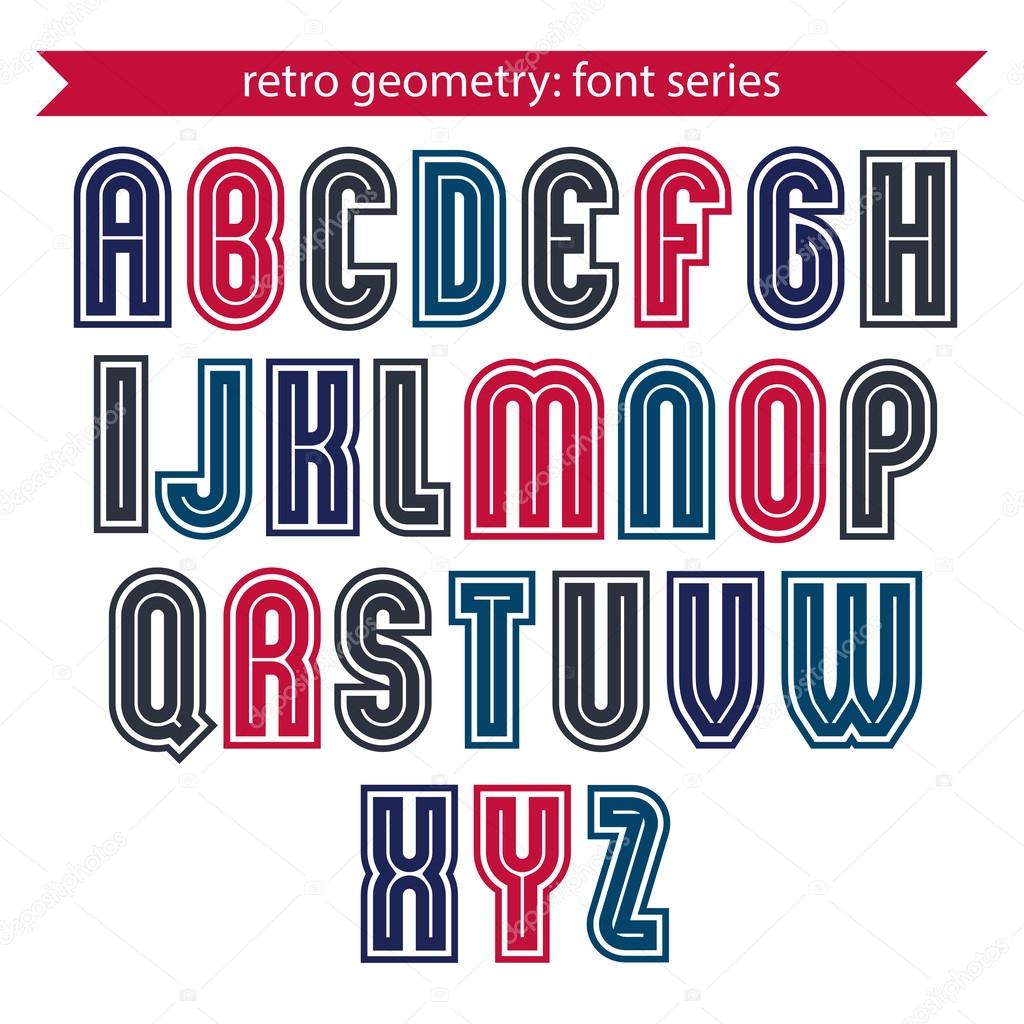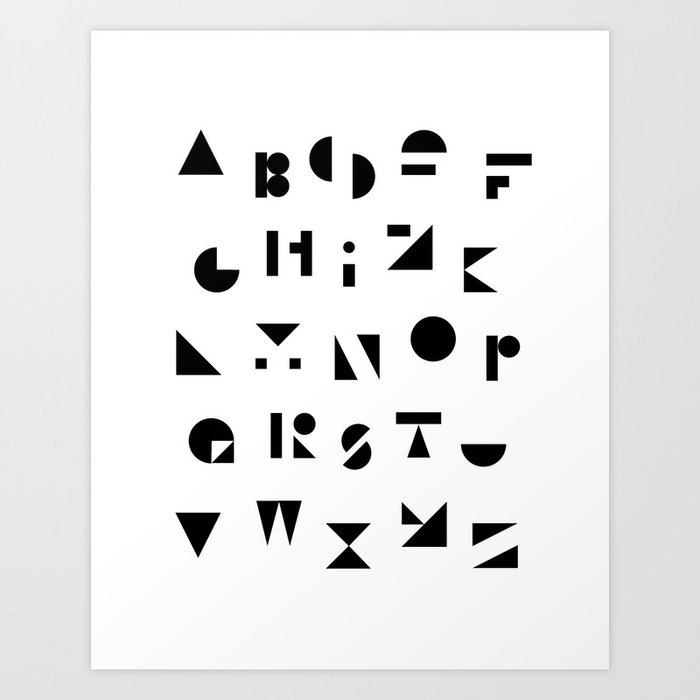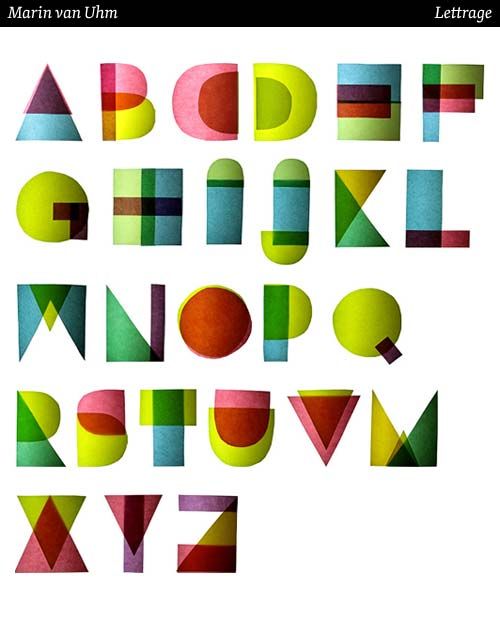
Геометрические шрифты — это.
.. Что такое Геометрические шрифты?- Геометрические шрифты
- Подгруппа рубленых шрифтов, имеющих постоянную или почти постоянную толщину штрихов.
геометрические брусковые шрифты — (Geometric Slabserif) Собирательное название шрифтов c прямоугольными засечками, построенных на основе простейших геометрических форм – окружности, квадрата, равностороннего треугольника. Эти шрифты появились в 20–30 х гг. ХХ в. как… … Шрифтовая терминология
геометрические гротески — (Geometric Sans) Собирательное название шрифтов без засечек [короткий штрих на торце основного штриха], построенных на основе простейших геометрических форма окружности, квадрата, равностороннего треугольника.
Эти шрифты появились в 30 х гг.… … Шрифтовая терминологияШрифты, поддерживающие юникод — Юникод Шрифт графический рисунок начертаний букв, знаков, иероглифов которые заключены в стандарте кодирования символов, позволяющие представить знаки многих письменных языков мира. В Юникод шрифте может быть заключён как один блок символов … Википедия
классификация шрифтов — В настоящее время общепринятая классификация шрифтов отсутствует, поэтому любая схема отражает личное мнение ее составителей. Наша классификация не исключение; не удивляйтесь, если обнаружите, что она отличается от тех классификационных… … Шрифтовая терминология
geometric slabserif — Геометрические брусковые шрифты (Geometric Slabserif) Собирательное название шрифтов c прямоугольными засечками, построенных на основе простейших геометрических форм – окружности, квадрата, равностороннего треугольника. Эти шрифты появились в … Шрифтовая терминология
geometric sans — Геометрические гротески (Geometric Sans) Собирательное название шрифтов без засечек [короткий штрих на торце основного штриха], построенных на основе простейших геометрических форма окружности, квадрата, равностороннего треугольника.